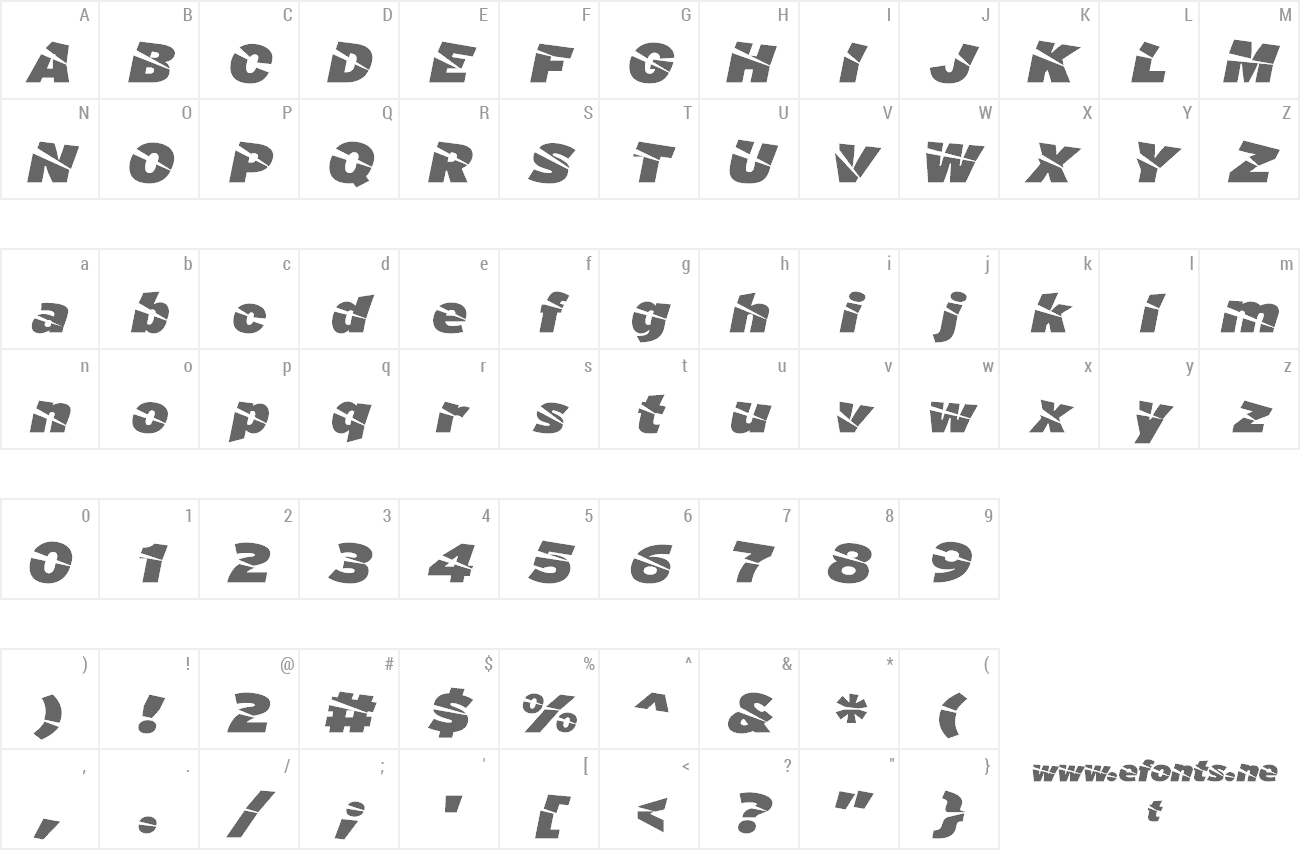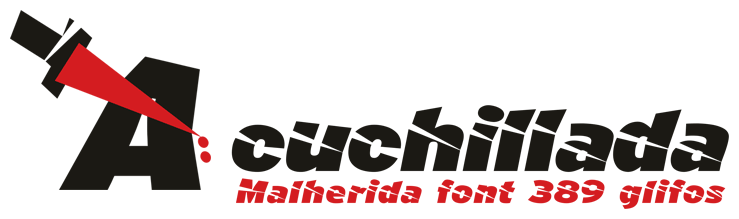
-La tipografía A cuchillada es un experimento expresionista del dolor del autor por la muerte prematura de un gran amigo. -Typography A knife is a pain expressionist experiment typographer by the untimely death of a great friend. • Sólo para uso personal. • Licencia comercial disponible por un donativo libre • Only for personal use. FULL VERSION & COMMERCIAL LICENSE: https://defharo.com/fonts/acuchillada-font/ |